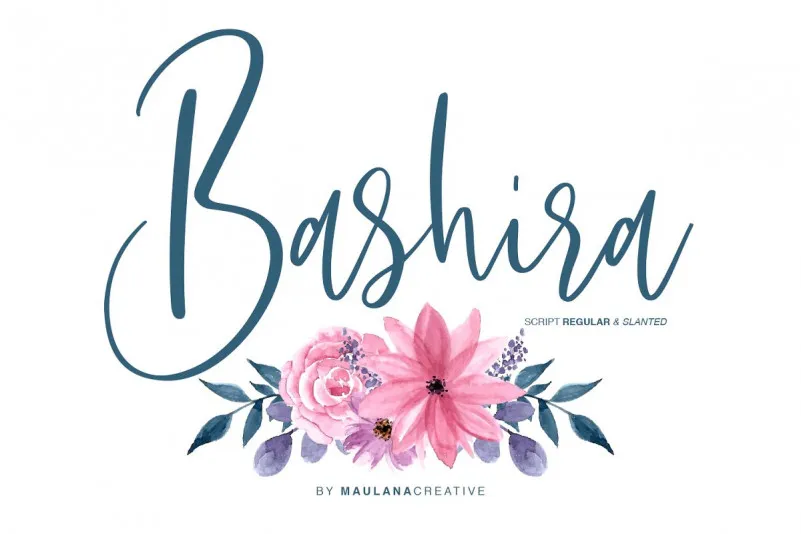
Bashira Handwritten Font – Download Grátis
Bashira Handwritten Font é uma maravilhosa escolha para aqueles que buscam uma fonte script com um toque autêntico e envolvente, perfeita para agregar um visual de alta qualidade a qualquer projeto gráfico. Com sua natureza elegante e fresca, esta fonte vem como uma ótima adição às categorias de logotipos, design editorial, capas de livros e sites. Desenvolvida pelo designer Maulana Creative, Bashira Handwritten oferece um toque de personalidade perfeito para os seus projetos. Este script moderno se adapta perfeitamente a várias aplicações como assinaturas, desenhos de cartão de visita, logotipos, citações em revistas ou livros e cabeçalhos para sites. Além disso, o conjunto vem com ligações incorporadas, proporcionando ainda mais opções de personalização. Com Bashira Handwritten Font, você pode garantir que cada projeto seja marcado por uma mão que escreveu. Ideal tanto para designers profissionais quanto iniciantes, esta fonte é um complemento impecável para trabalhos criativos e um recurso valioso em sua paleta de fontes.